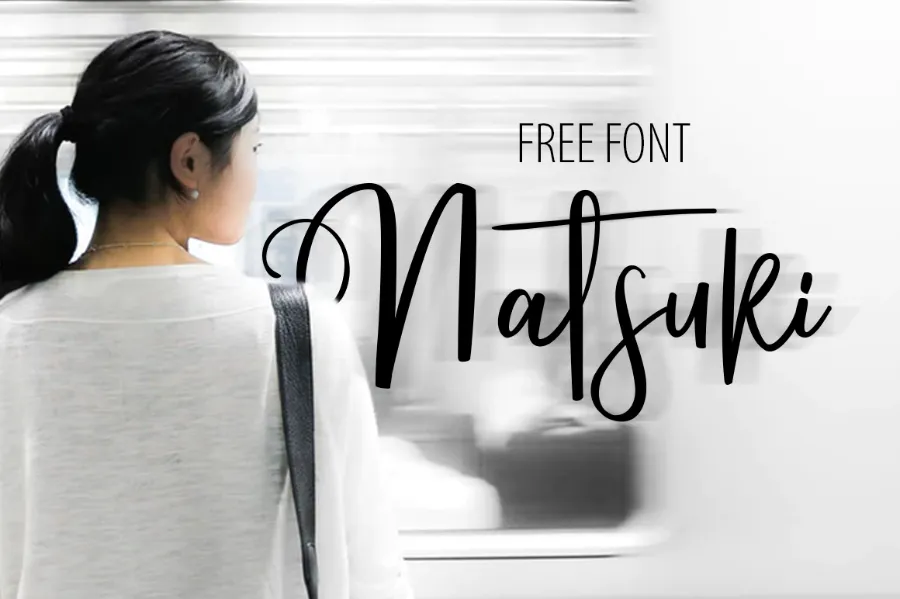
Natsuki Script Font – Download Grátis
A Natsuki Script Font é uma criação cuidadosamente meticulosa do designer Olexstudio, disponível agora no seu formato de script moderno. Cada letra foi desenhada com todo carinho para tornar sua mensagem ainda mais bonita e atraente. Esta fonte perfeita combina estilo moderno que se adapta perfeitamente a uma variedade de projetos como convites, cartas de boas-vindas, panfletos, cartões de nome, citações, cabeçalhos de blog, marca, logotipo, moda e roupa. Além disso, ela é ideal para letras, papelaria e muitos outros tipos de trabalho gráfico. Com a Natsuki Script Font, você encontrará uma solução única que fará suas criações ficarem ainda mais belas e atraentes.